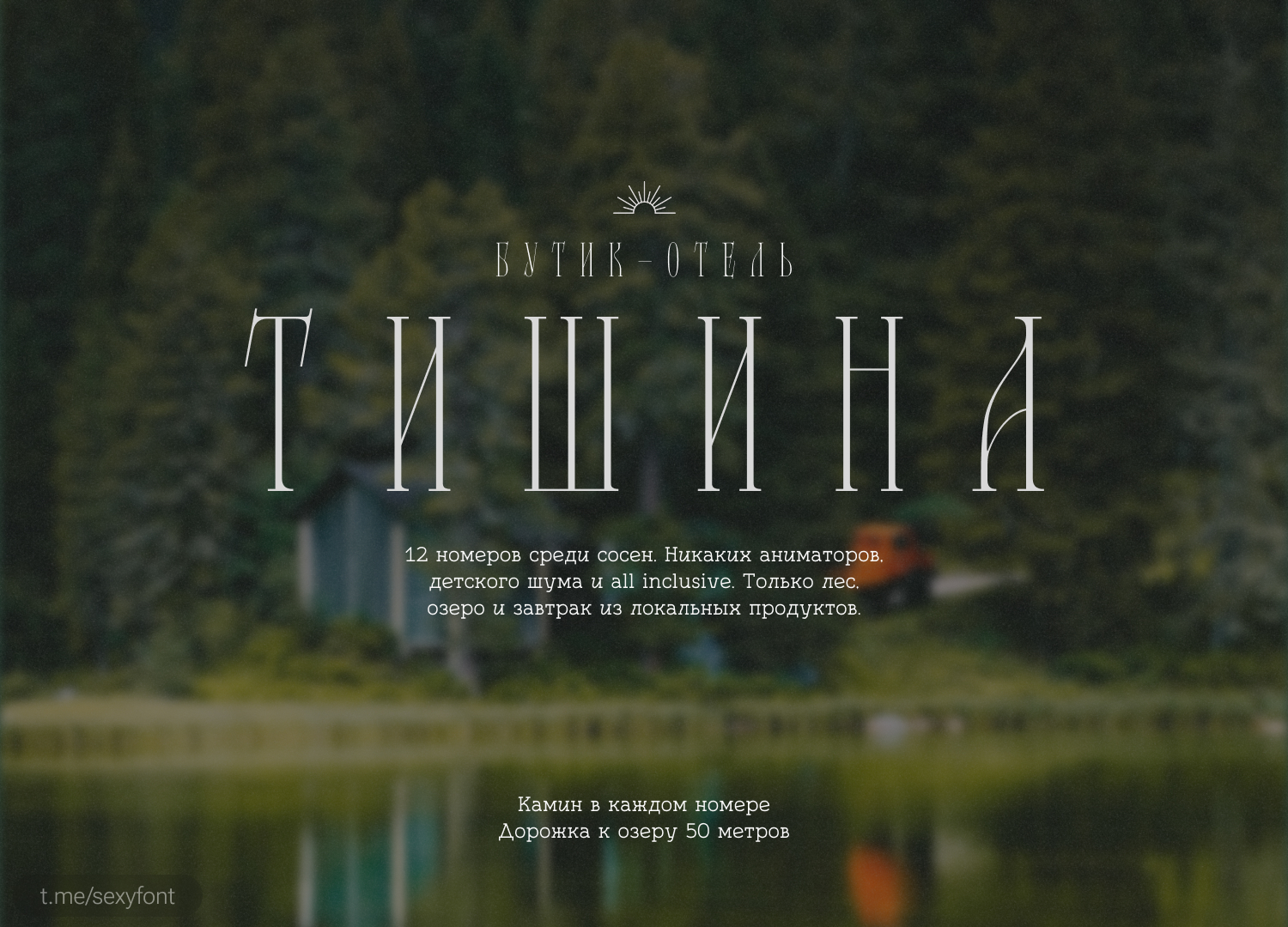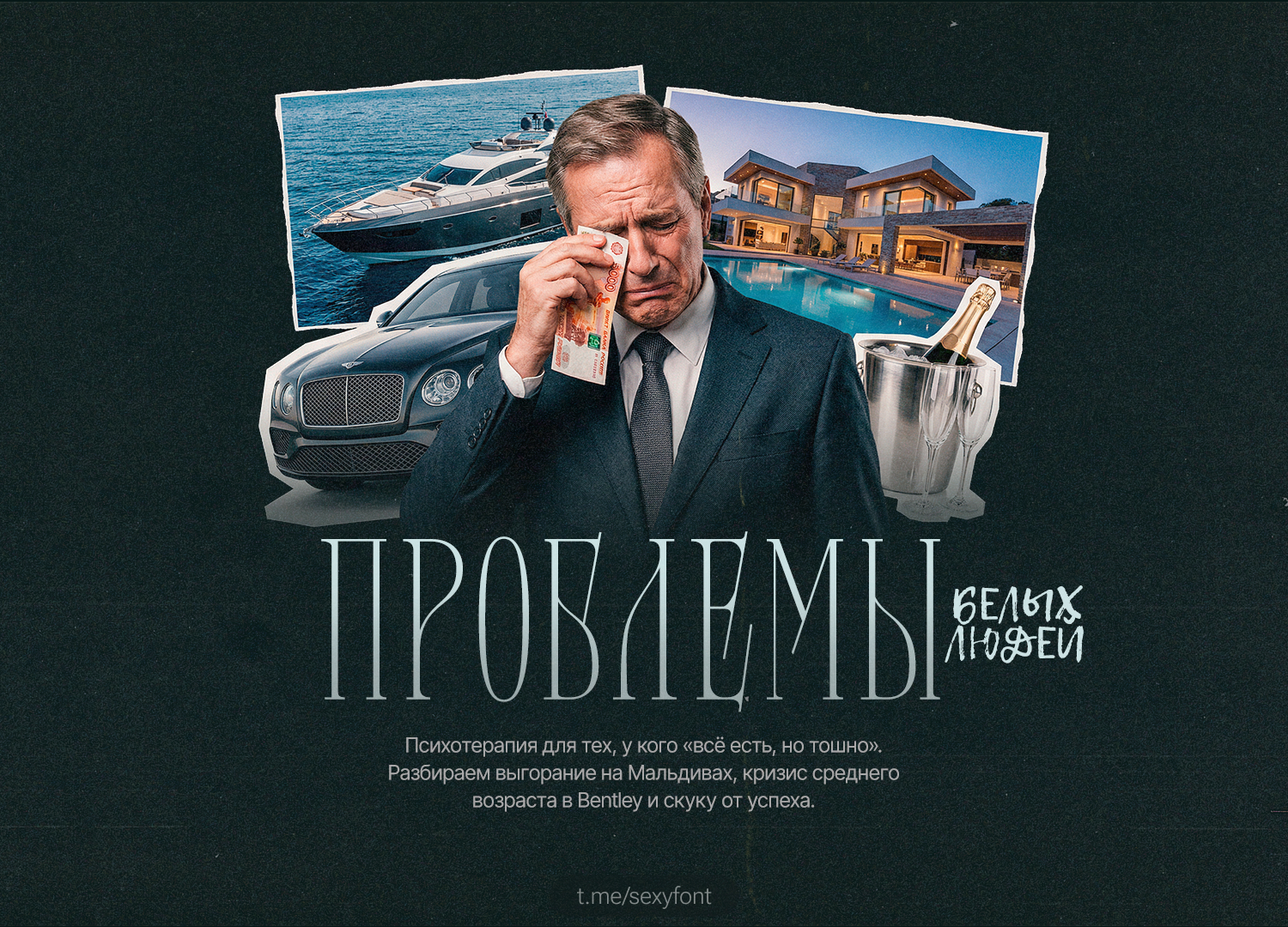
Бесплатный шрифт Thaloria⁠⁠
Доделал новую презентацию. Шрифт Thaloria. Акцидентная антиква с вытянутыми пропорциями, вдохновленная журнальными обложками в стиле ар-нуво и некоторыми формами старославянских букв. Асимметричные, шиповидные засечки придают шрифту лёгкий готический характер, а высокий контраст делает его более изысканным.